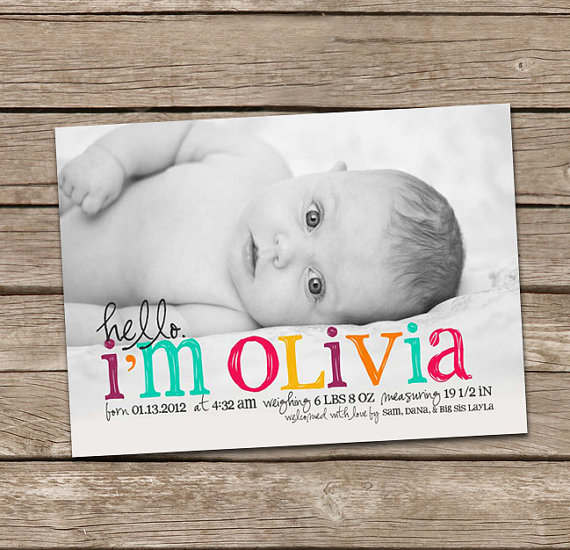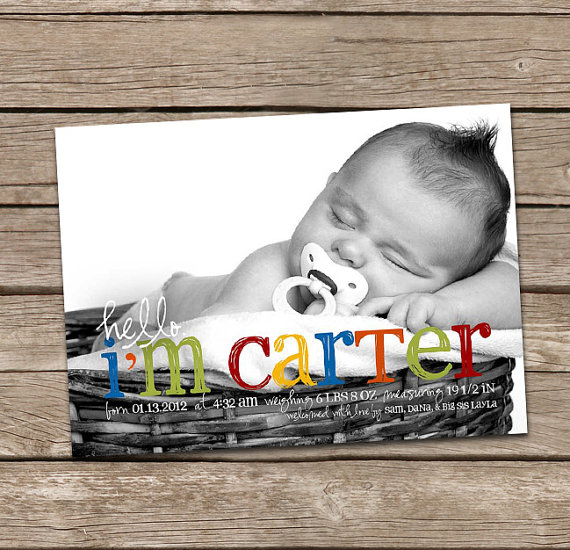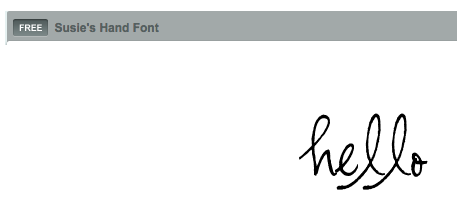
Erkennt jemand diese beiden Schriftarten?
ich habe auf einer amerikanischen Karte zur Geburt (Birth Announcement) zwei Schriftarten gefunden, die ich seither suche. Ein Bild habe ich angehängt.
Ich würde mich sehr freuen. wenn mir jemand weiterhelfen könnte. Die untere Schriftart scheint nur aus Kleinbuchstaben zu bestehen, da ja das Apostroph auf gleicher Höhe ist.
Hier sind noch andere Buchstaben zu sehen …
Danke für deine Hilfe! Ich habe noch ein bisschen gestöbert unter "upper and lower case" und bin auf 2peas old type gestoßen - ich glaube das könnte sie sein!